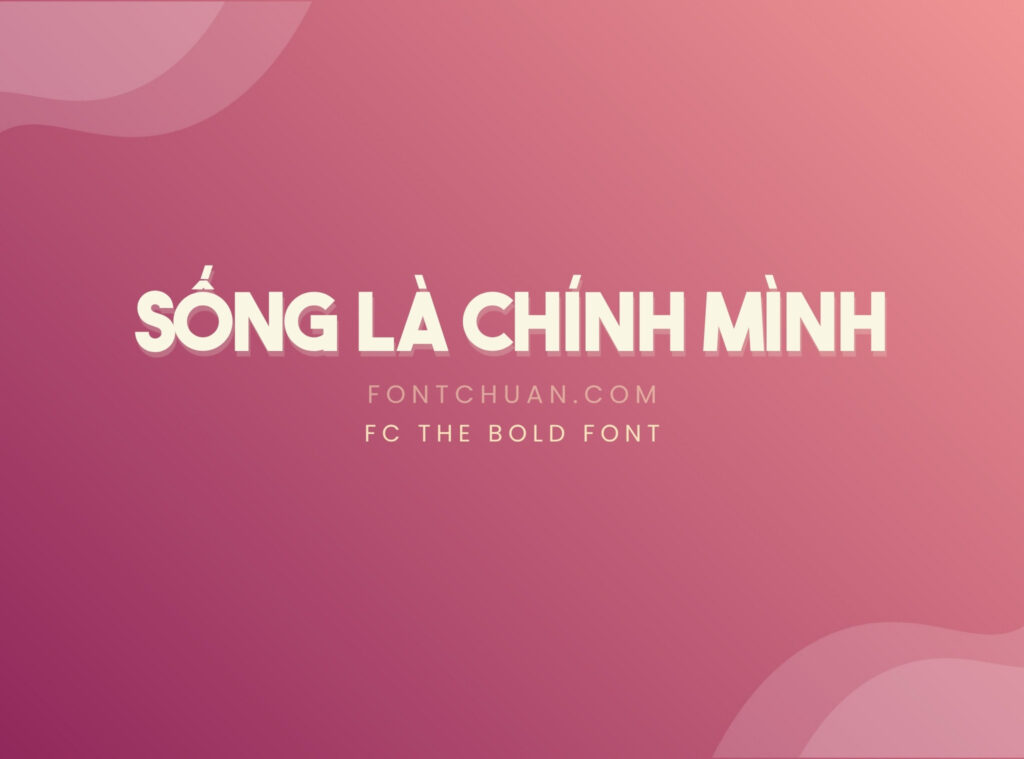
The Bold Font là một kiểu chữ sans-serif đậm, được thiết kế bởi nhà thiết kế logo và đồ họa Sven Pels vào năm 2015. Lấy cảm hứng từ sự tò mò về các nét chữ có độ rộng bằng nhau trong kiểu chữ, The Bold Font mang đến một thẩm mỹ mới mẻ, phá vỡ các quy tắc thiết kế truyền thống và tạo ra sự nhất quán trong các nét chữ.
Font FC The Bold Font Việt Hóa do Team Font Chuẩn việt hóa thế hệ mới và chia sẻ miễn phí. Hỗ trợ tốt cho tiếng Việt, tiếng Anh và nhiều ngôn ngữ Latin khác, mở rộng khả năng ứng dụng cho nhiều dự án quốc tế, đáp ứng nhu cầu đa dạng của bạn đọc và hỗ trợ ứng dụng thực tế trong các dự án thiết kế.
Với cấu trúc chữ đậm, dày, và tròn trịa, các nét chữ có độ rộng bằng nhau và thiết kế tinh tế, The Bold Font phù hợp cho các thiết kế logo, tiêu đề, poster và các ấn phẩm quảng cáo khác. Đặc biệt, trong những dịp kỷ niệm hay tri ân thầy cô, font này khi làm Font ngày Nhà giáo Việt Nam để tạo nên sự hài hòa giữa vẻ mạnh mẽ, hiện đại và sự trang trọng, ý nghĩa trong thiết kế.